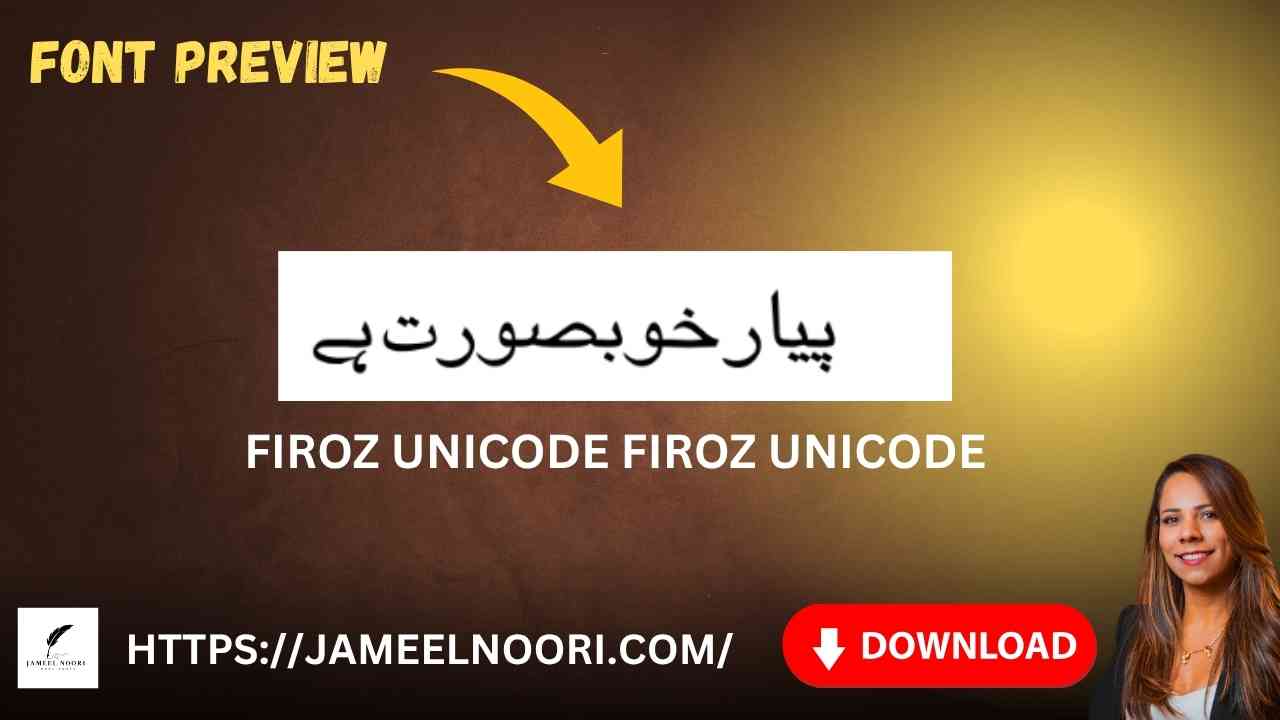
Agar aap Urdu me typing ke liye aik clean aur Unicode-supported font talash kar rahe hain, to Download Urdu font Firoz Unicode aap ke liye best choice hai. Ye font especially un users ke liye design kiya gaya hai jo Inpage, MS Word, ya design software me Urdu likhna chahte hain.
Download Urdu font Firoz Unicode ki Key Features & Compatibility
Download Urdu font Firoz Unicode ka Use Kahan Kiya Jata Hai?
Yeh font Urdu typing ke liye specially develop kiya gaya hai aur iska use bohot jagahon par hota hai:
- Urdu official documents
- Books aur eBooks
- News websites aur blogs
- Inpage aur CorelDraw Urdu design
- Educational materials for Pakistani students
Agar aap Lahore ya Karachi me graphic designer hain, to aap ko yeh font zaroor try karna chahiye.
Why Download Urdu font Firoz Unicode is Expert Choice for Urdu Writers
Aaj kal Urdu writing aur digital content creation me Unicode fonts kaafi important ho gaye hain. Aur Firoz Unicode un sab me aik expert-level font mana jata hai.
Is font ki kuch major advantages yeh hain:
- Unicode format me hone ki wajah se website aur app compatibility perfect hai
- Clear aur neat appearance, jise parhna asaan hota hai
Top 5 Benefits of Using Firoz Unicode
- Unicode-based Urdu typing for clean compatibility
- Lightweight, fast, and easy-to-read
- Suitable for documents, design, and books
Conclusion (Download Urdu Font Firoz Unicode – Complete Guide 2025)
Akhir me, Firoz Unicode ek stylish aur clear Urdu font hai jo professional designing, publishing, aur digital content creation ke liye best choice hai. Iska Unicode format ensure karta hai ke yeh har platform aur device par perfectly render ho, chahe aap Windows, Mac ya mobile par use karein. Is font ki readability aur attractive style isay both personal aur commercial projects ke liye ideal banati hai. Agar aap apne Urdu text ko modern aur elegant touch dena chahte hain, to Firoz Unicode ka download aur use aap ke liye ek smart decision hoga.